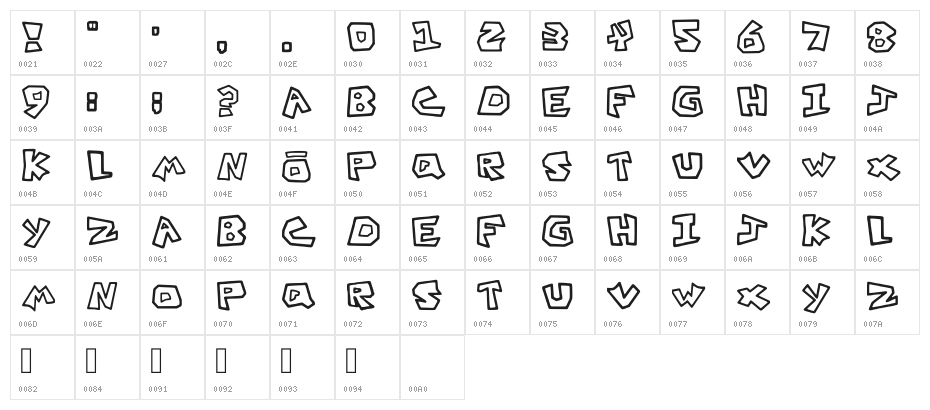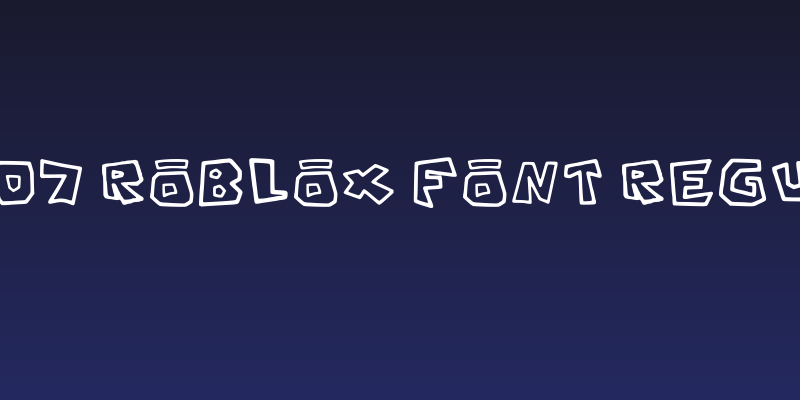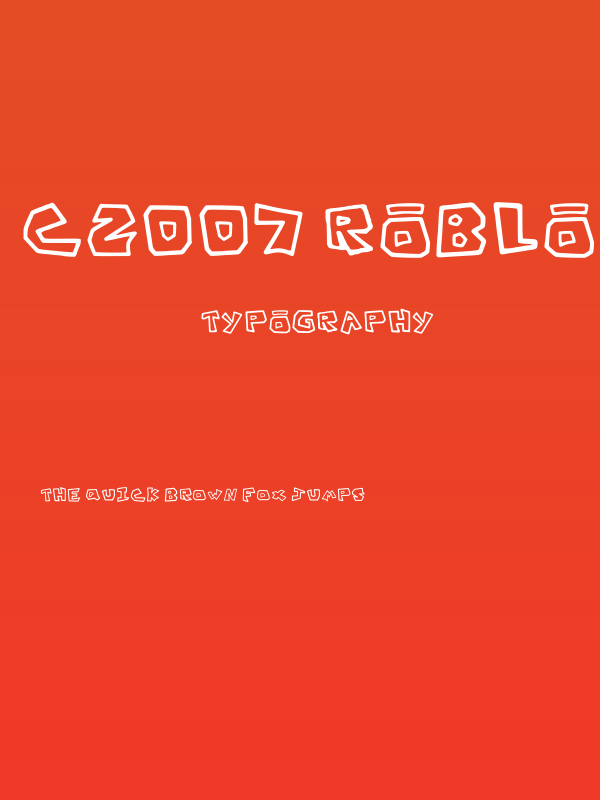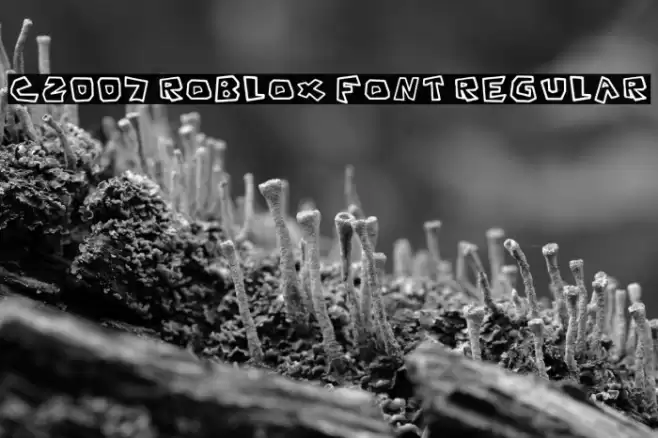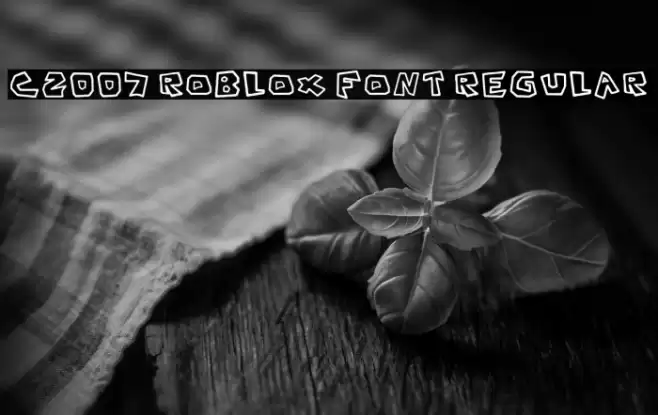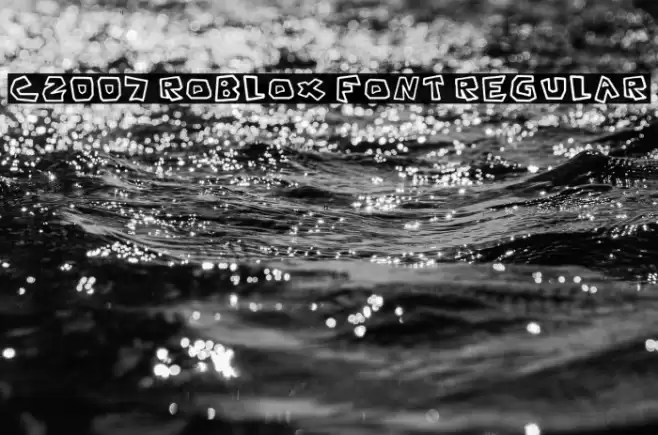
C2007 Roblox Font Regular Font
| नाम | C2007 Roblox Font Regular |
| फ़ॉन्ट परिवार | C2007 Roblox Font |
| Style | C2007RobloxFont-Regular |
| श्रेणियाँ | Kids |
| समग्र शैली | Playful, Cartoonish |
| उपयोग का मामला | Headlines, Logos, Posters |
| सुझाए गए प्रोजेक्ट | Ideal for children's books, comic strips, video game graphics, and playful branding. |